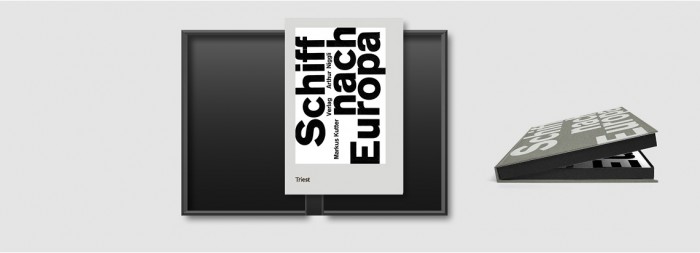
Neuauflage «Schiff nach Europa»
Neuauflage eines Kultbuchs
Markus Kutters Roman Schiff nach Europa – «optisch organisiert» von Karl Gerstner – «nimmt früh eine experimentelle Position ein, die in der Buchgestaltung erst einige Jahre später zum Durchbruch gelangen wird», schrieb François Rappo. Es ist durch seine auf den Text abgestimmte Typografie als Meilenstein der Schweizer Buchgestaltung anzusehen und wurde 1957 als Schönstes Schweizer Buch  ausgezeichnet.
Der als synthetischer Roman bezeichnete Inhalt (eine Schiffspassage von New York nach Europa auf der später gesunkenen Andrea Doria) besteht aus verschiedenen Textsorten – Erzählung, Drama, Gespräch und Monolog. Markus Kutter stellte sich bereits beim Schreiben vor, dass der Text typografisch entsprechend inszeniert werden müsste. Karls Gerstner beschrieb diese Aufgabe als «persönliches Experiment» und «besondere Delikatesse.»
Die Freude, «integrale Typographie» umgesetzt zu haben, ist dem Buch anzumerken und springt auf die Leser über.
Das Buch ist seit Jahren vergriffen und von Sammlern gesucht. Durch die Neuauflage wird es vielen erstmals möglich sein, das Kultbuch endlich selbst in den Händen zu halten. Der Reprint ist originalgetreu, ein beidseitig bedruckter Schutzumschlag liefert sowohl das ursprüngliche Cover als auch die aktualisierte Version mit einem Kommentar von Felix Wiedler.